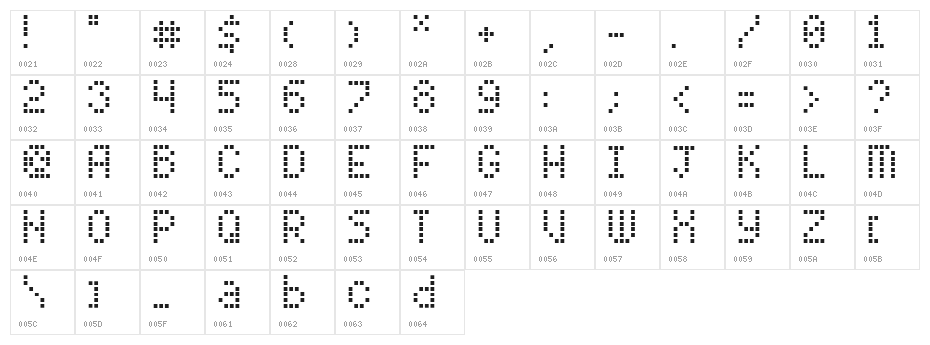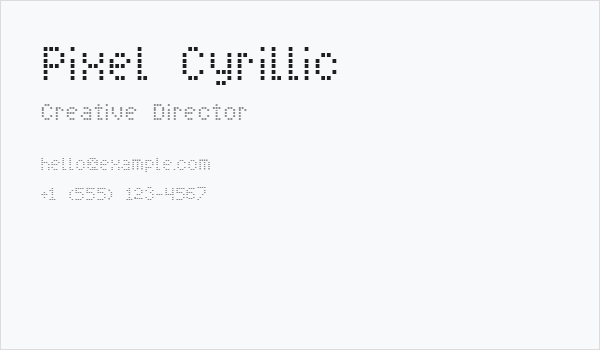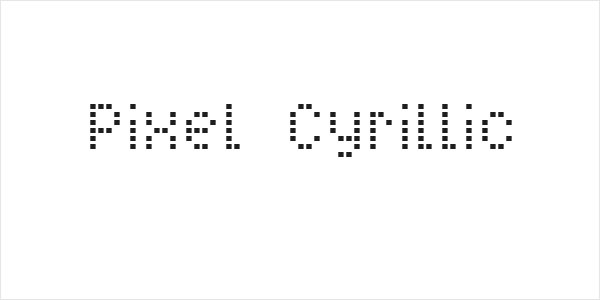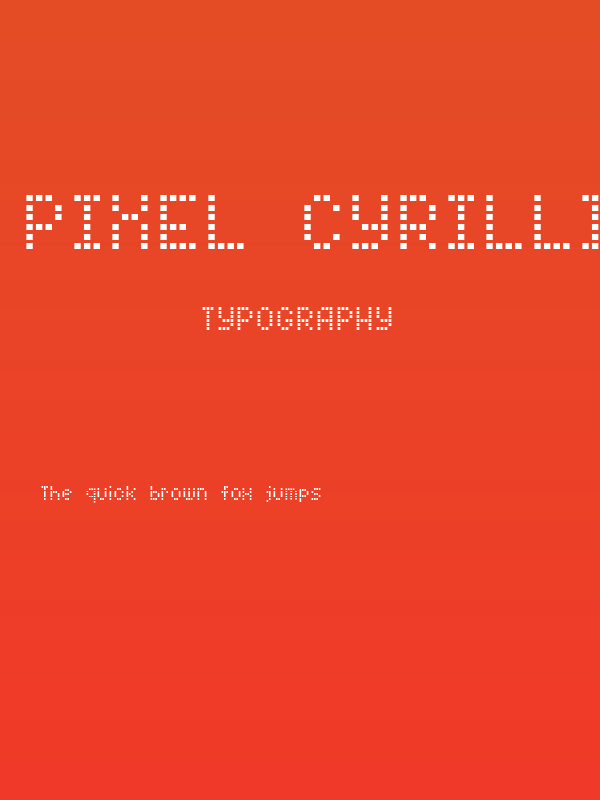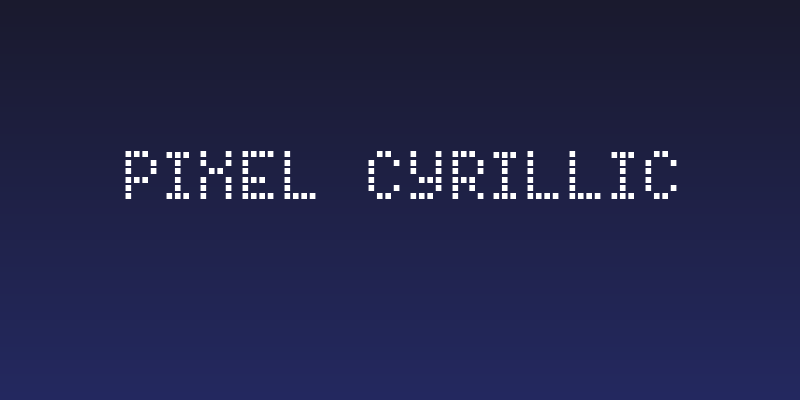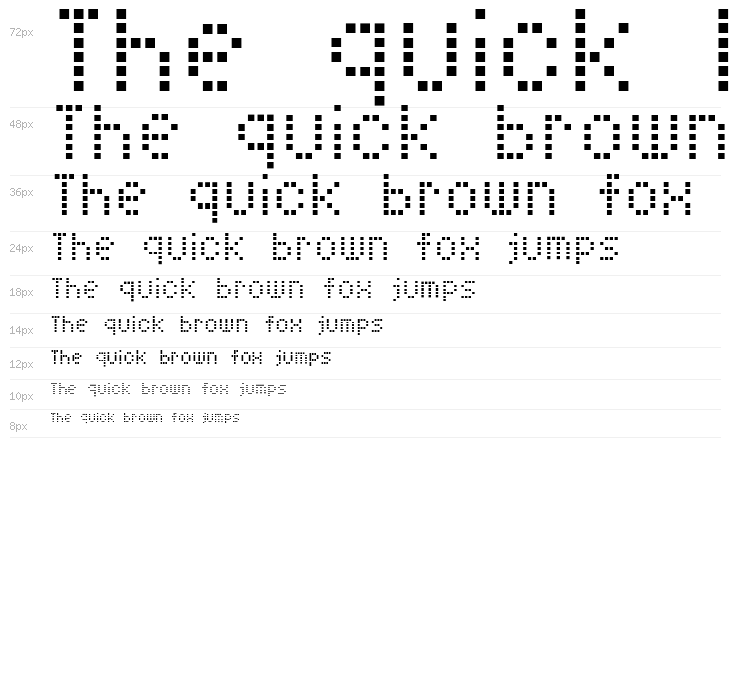
Pixel Cyrillic Font
✎ Dotted
| 整体风格 | Retro, Digital |
| 推荐项目 | Ideal for retro video game designs, tech-themed posters, digital art projects, and any creative work that seeks to capture a vintage digital aesthetic. |